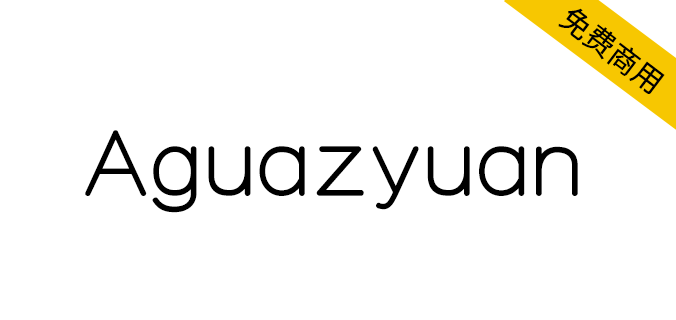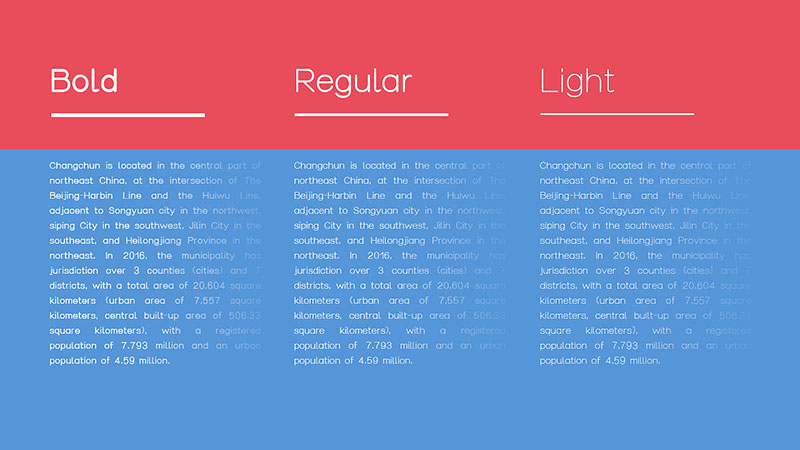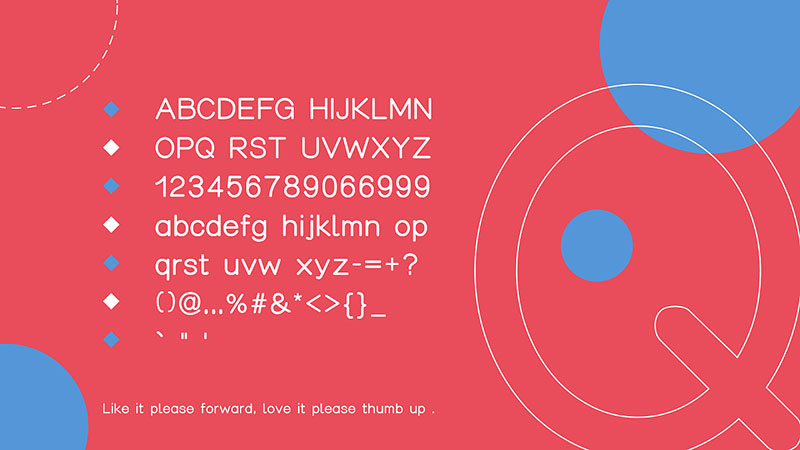
【Aguazyuan 阿瓜准圆体】非常适合大篇幅英文正文出现
2020年9月份一整月,开发了阿瓜准圆体【Aguazyuan】,共三款字型,本套英文字库终身免费商用,本款字体非常适合大篇幅英文正文出现,良心力作,祝愿设计师同行小伙伴们多多升值【升职】,多多加薪【赚票子】。
【Aguazyuan 阿瓜准圆体】非常适合大篇幅英文正文出现